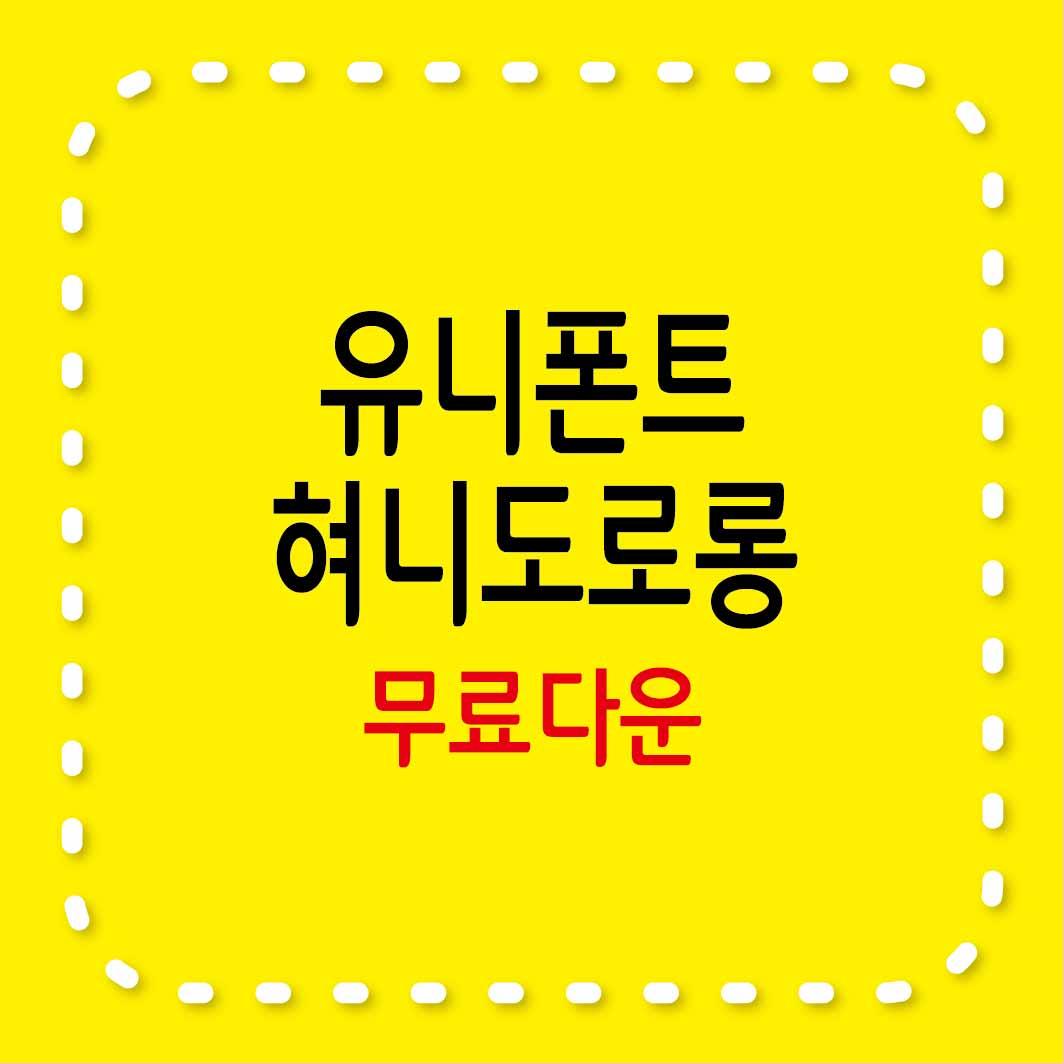
유니폰트
유니폰트는 또박또박 글씨를 써 내려가는 학생의 감성을 담은 손글씨 폰트입니다. 귀여운 손글씨지만 정형화된 느낌의 본문용 서체로써 재미있는 글씨체입니다.
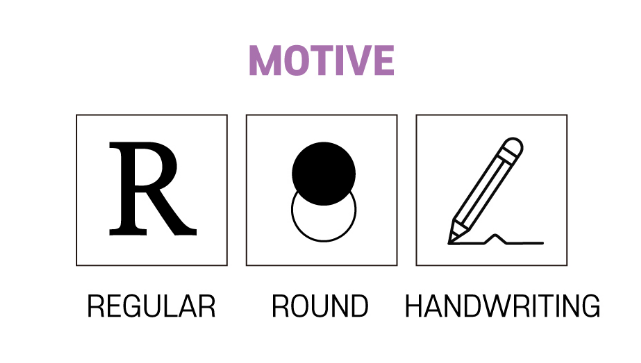
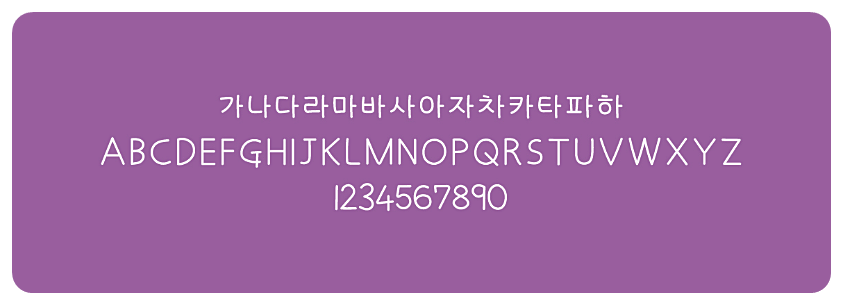
유니폰트의 특징 1
자연스러운 곡선을 통한 부드러운 이미지를 더했습니다.
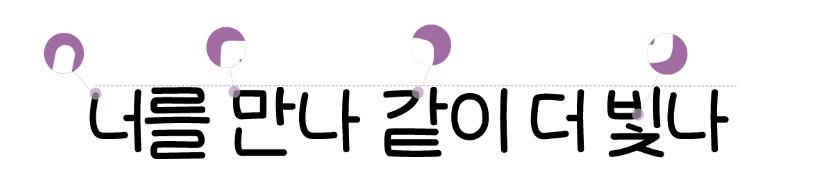
특징 2
아기자기한 손글씨 느낌의 서체입니다.
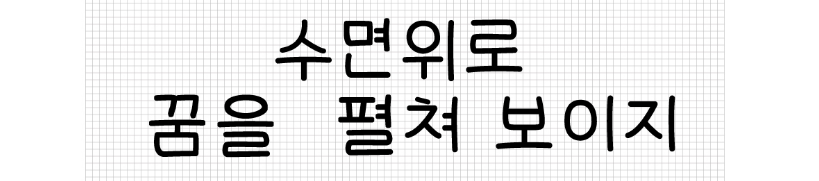
예시
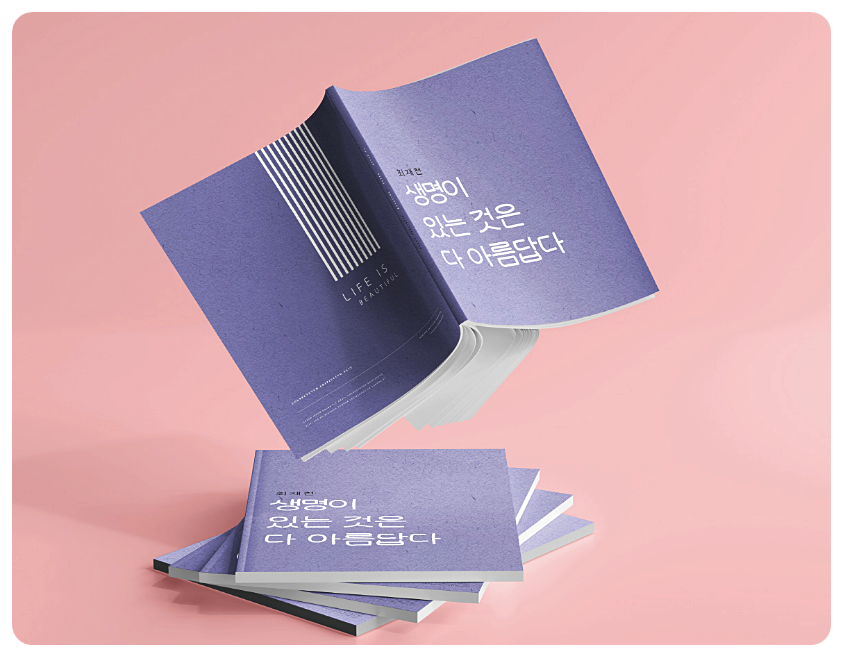
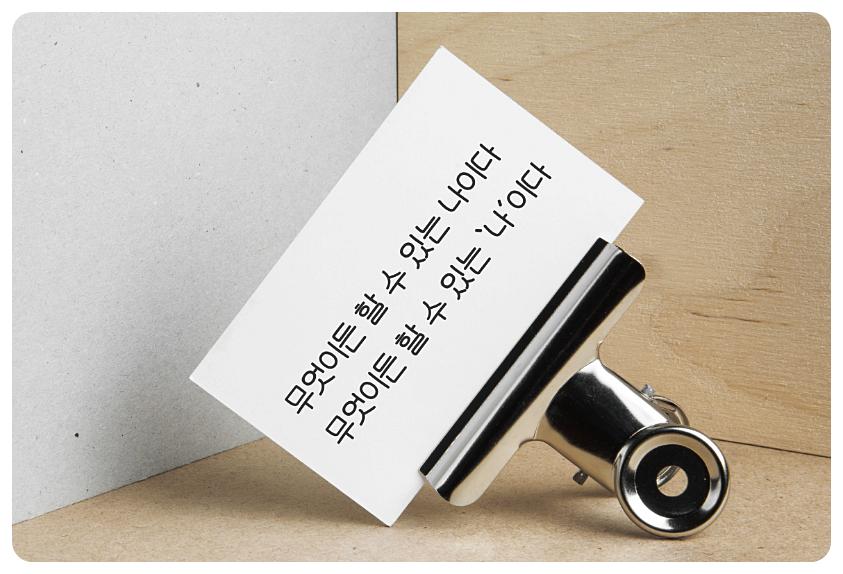
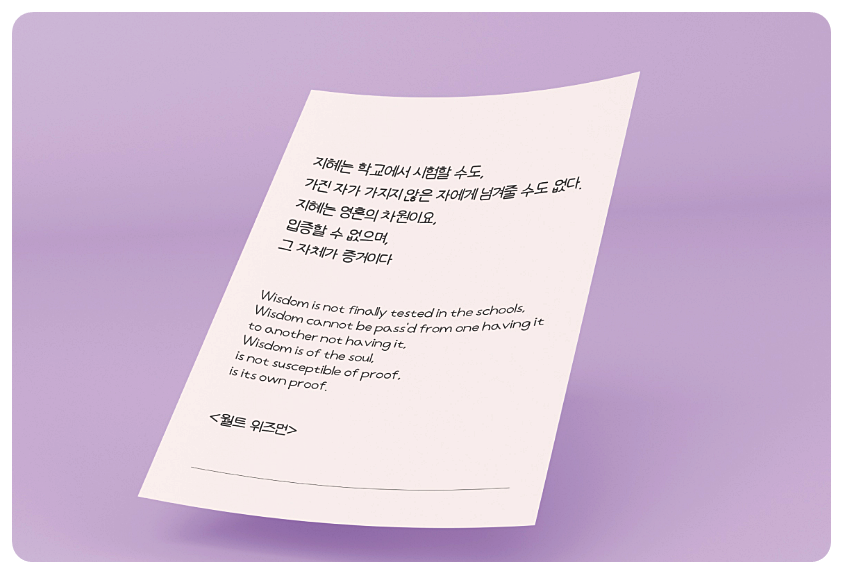
혀니도로롱
혀니도로롱 서체는 상대방에게 자신의 감정을 표현하고자 할 때 유용하게 사용할 수 있는 폰트입니다.
디자이너 hyuny가 제안하는 사춘기의 감성을 지닌 혀니도로롱 서체는 제목용 서체로서 귀여운 손글씨 형태의 재미있는 느낌으로 표현하였습니다.
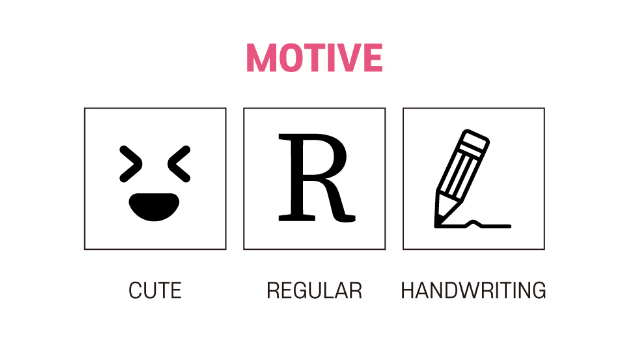
혀니도로롱 서체의 특징 1
자연스러운 곡선을 통한 부드러운 이미지를 표현했습니다.
특징 2
획일화된 높이가 아닌 손글씨 느낌의 귀여운 이미지의 서체입니다.
예시